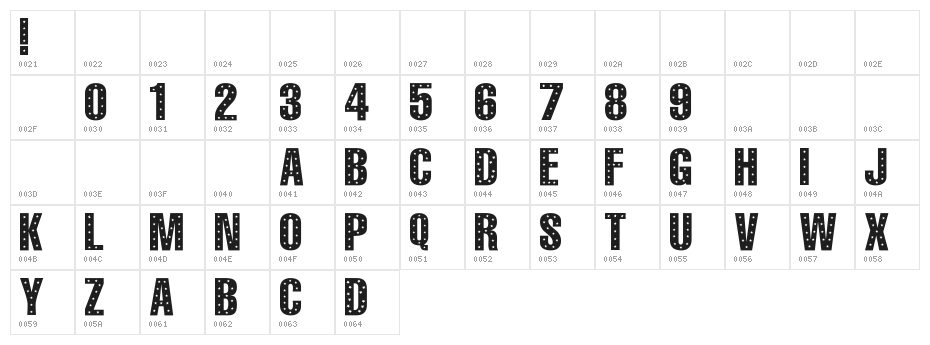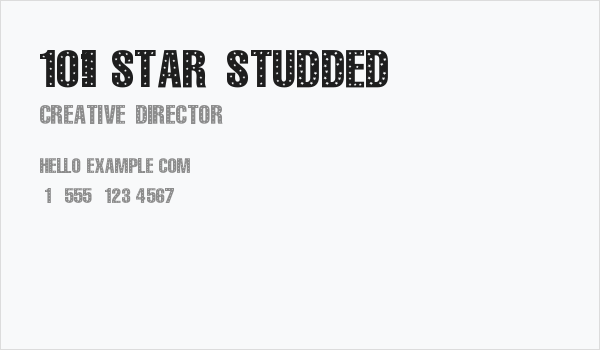
101! StaR StuDDeD Font
| Progetti proposti | Ideal for party invitations, children's book covers, festive banners, and any project needing a fun, decorative touch. |